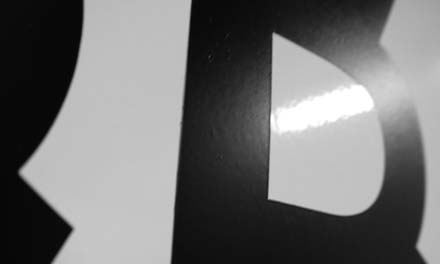
Pedro FalcãoArtista plástico, designer gráfico.Nasceu em 1971 em Caldas da Rainha. Vive e trabalha em Lisboa. Representado pela Galeria Ste, Coimbra.
Faz abstracção a partir de fontes construtivistas, neo-plasticistas, minimalistas ou Op, geradas a partir da investigação gráfica e do computador. Grelhas geométricas ortogonais ou malhas curvilíneas surgem como pormenores de uma "realidade maior". Fragmentos de um alfabeto vazio de sentido e sem função prática. A exposição "Letterscape 1" (Museu de História Natural, Sala do Veado, 2002) assinalou na obra de Pedro Falcão o aparecimento de uma linguagem cuja orientação lhe foi fornecida pelos estudos universitários e sua prática profissional enquanto designer gráfico. Enquanto a sua primeira relação com a música pop-rock era intuitiva, utilizando temas e ícones de imediato reconhecimento, a investigação em torno dos elementos fornecidos pela história e cultura do design gráfico e da tipografia, define-se em campos mais eruditos. Na série "Dupla Sombra" são os fragmentos de letras que, desdobrando-se no espaço de representação, adquirem valias quase arquitectónicas. Neste texto, a definição prévia dos campos de intervenção (passada ou presente) de Pedro Falcão, permite-nos analisar os seus temas e níveis de actuação dando autonomia conceptual a cada um deles. Embora baseando-se na letra impressa e apesar do esvaziamento de significados que evidenciam as metodologias de associação empregues por Pedro Falcão assumem uma forte relação com a longa história dos exercícios caligráficos. E, nesse sentido, estas obras estão mais perto da essencialidade concentrada do "entrelac" das capítulares medievais cristãs do que da extensão dos intrincados exercícios da caligrafia árabe, mais perto da mancha da composição tipográfica barroca ou da vocação programática da poesia visual do concretismo que do desregramento tipográfico futurista. Organizadas em friso decorativo ou banda decorativa, reduzidas a fragmentos ou (como aqui) apresentadas na sua inteireza, as letras recuperam a possibilidade de exibição de um lado o valor gráfico puro, destino que nunca pode ser atribuído a uma letra que se lê as letras ganham assim um valor plástico puro na página-tela e, ao mesmo tempo, sugerem a possibilidade de uma existência puramente virtual que parte da exploração dos recursos tecnológicos da página-ecrã onde são concebidas. Respeitando uma grelha de composição, determinada pela pauta horizontal onde se sustentam as escritas ocidentais, Falcão não rompe com a tradição compositiva da escrita ocidental nisso negando a experiência da ruptura futurista ou mostrando-se mais moderado que as experiências barrocas ou concretistas de que falámos. |